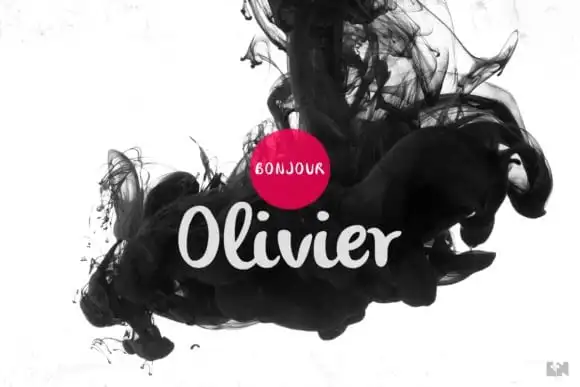
A fonte Olivier é inspirada nas letras pintadas feitas com tinta preta. Sua elegância vem do suave movimento de uma garrafa de vinho, evocando a fluididade e a liberdade que esse líquido animal possui. Inspirado em sua forma viva e vibrante, essa fonte permite que as linhas base se deslocuem para além da média, alterando os pés, os corpos e os capados para um toque orgânico e descontraído. Essa característica dada às letras cria uma sensação de leveza e criatividade, proporcionando um toque alegre e divertido à qualquer projeto gráfico que ela possa adornar. Não importa qual projeto seja, Olivier trará ao seu design uma presença única e vibrante.